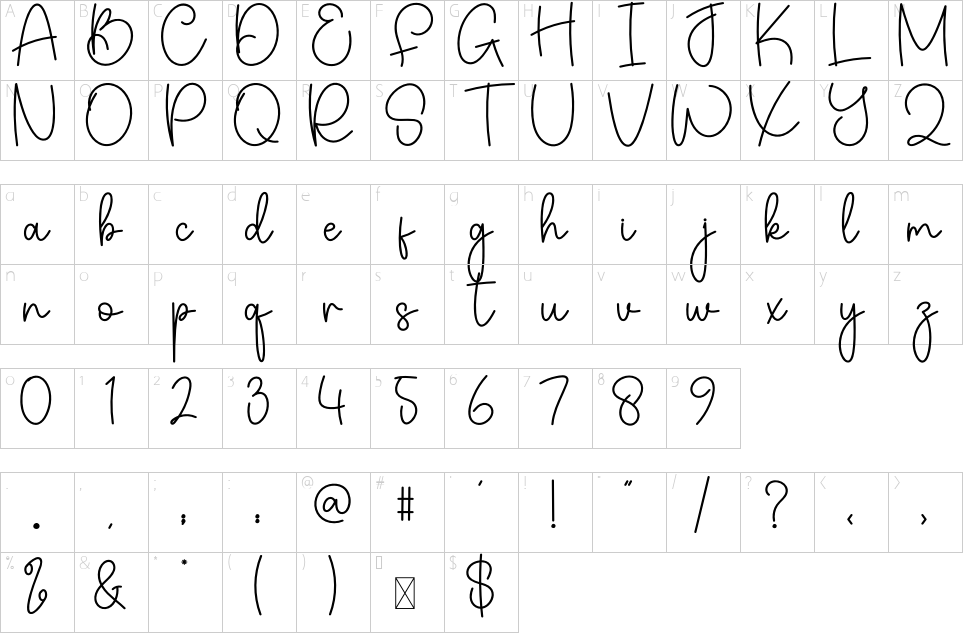
Esta página apresenta a Graphic Script Font – uma elegante escolha para designers e criadores de conteúdo que valorizam personalidade e grafição nas suas criações digitais. Ela foi projetada pelo designer desconhecido, Scratchones, e já foi baixada 1.044 vezes pelos amantes da tipografia. A Graphic Script é uma fonte gráfica perfeita para anúncios de moda, design editorial ou qualquer projeto que valorize um estilo de escrita criativo e vibrante. Suas linhas fluidas e curvas sofisticadas permitem que você personalize seu trabalho de maneira única e atrativa. A Graphic Script é uma fonte versátil e adequada para projetos diversos – seja para criar cartazes, flyers ou até mesmo páginas web digitais. Com ela em sua coleção de fonts, o design está sempre em alta! Descubra por si mesmo a potencial deste recurso gráfico único, que será um complemento valioso à sua biblioteca de fontes. Descarregue agora esta fonte gratuita e comece criando hoje.